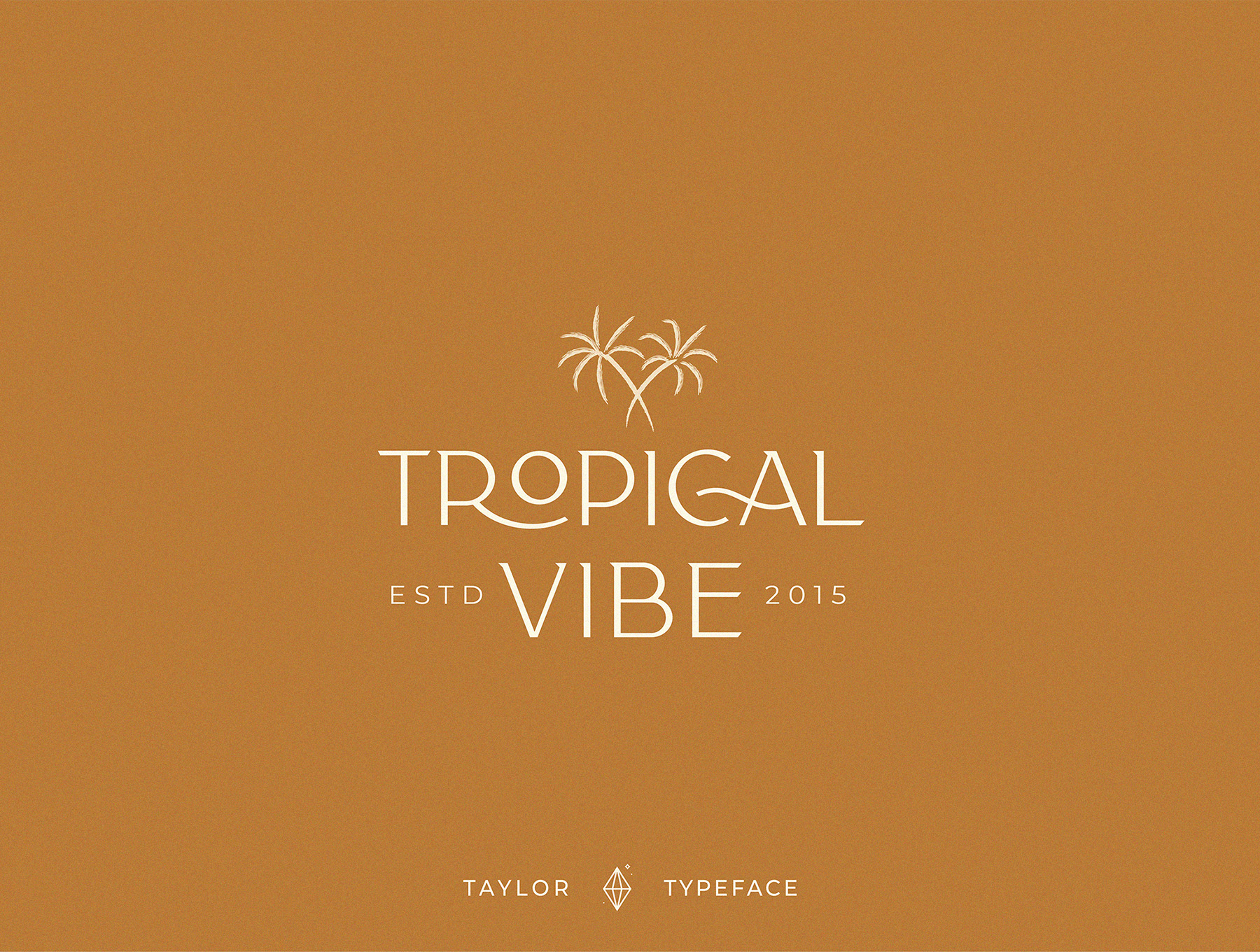
优雅泰勒是美丽的连写,万吨特种替代字形,装饰品和多语言支持,简约的摩登优雅的复古字体,优雅泰勒字样
优雅泰勒是美丽的连写,万吨特种替代字形,装饰和多语言支持的简约现代优雅的复古字体。这是一个非常通用的字体,在大尺寸和小尺寸的伟大工程。优雅泰勒是完美的品牌项目,标志设计,服装品牌,产品包装,杂志标题,或仅仅作为一种时尚的文本叠加到任何背景图片。